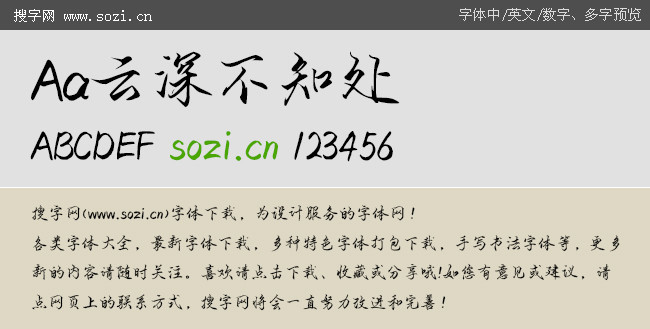
Aa云深不知處(非商業(yè)使用)
搜字網(wǎng)給大家提供一款A(yù)a云深不知處(非商業(yè)使用)中文字體下載,該字體是一款手寫中文字體,這款字體字形瀟灑大方,干凈利落,適合包裝設(shè)計(jì)、書裝設(shè)計(jì)、海報設(shè)計(jì)等應(yīng)用(此字體為個人非商用版,商用可以聯(lián)系QQ:1006760504)。